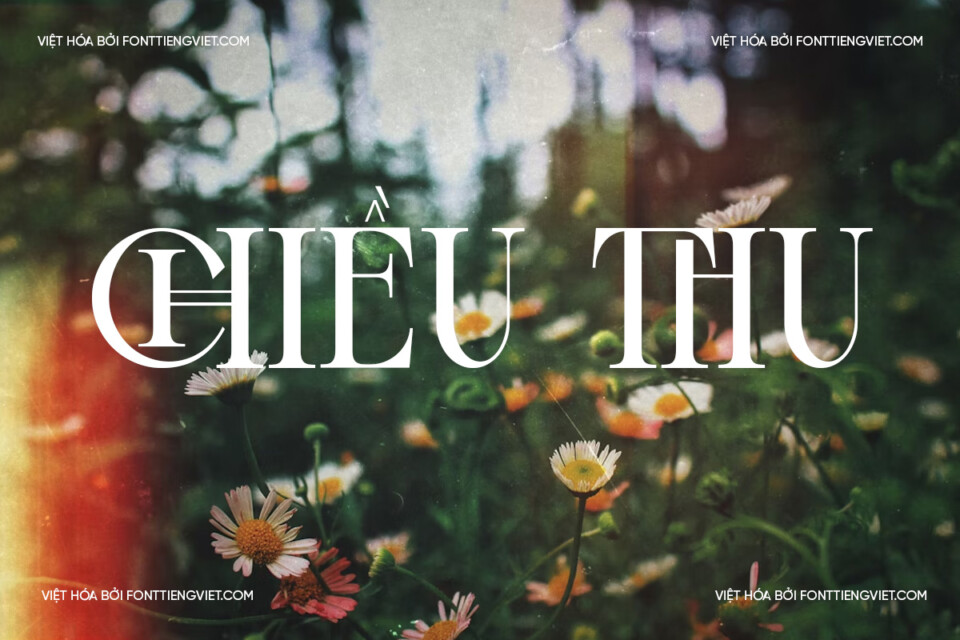
Font Việt hóa 1FTV VIP Lorenna
Chào mừng các bạn đến với thế giới sáng tạo nơi những con chữ không chỉ để đọc mà còn để cảm nhận vẻ đẹp nghệ thuật sâu sắc. Trong cộng đồng thiết kế đồ họa tại Việt Nam hiện nay, việc tìm kiếm một bộ Font Miễn Phí có hỗ trợ tiếng Việt hoàn chỉnh luôn là ưu tiên hàng đầu của các bạn học sinh và sinh viên. Hôm nay, chúng ta sẽ cùng khám phá bộ Font Việt hóa 1FTV VIP Lorenna, một siêu phẩm mang phong cách thanh lịch, hiện đại và vô cùng chuyên nghiệp. Đây là lựa chọn lý tưởng cho những ai đang muốn nâng tầm các bài thuyết trình, dự án học tập hay những ấn phẩm truyền thông cá nhân một cách tinh tế nhất.
Khám phá đặc điểm nổi bật của Font Việt hóa 1FTV VIP Lorenna
Bộ Font Việt hóa 1FTV VIP Lorenna được biết đến là một phông chữ thuộc phong cách Serif (có chân) nhưng lại mang hơi hướng đương đại rất rõ nét. Điểm đặc trưng của bộ font này chính là sự kết hợp hoàn hảo giữa những đường nét thanh mảnh và những nét đậm chắc chắn, tạo nên một tổng thể hài hòa và dễ nhìn trên nhiều nền tảng khác nhau.
Vẻ đẹp sang trọng và tính ứng dụng cao
Lý do khiến Font Việt hóa 1FTV VIP Lorenna trở nên “VIP” trong mắt người dùng chính là khả năng truyền tải thông điệp một cách lịch sự và trang trọng. Các ký tự được chăm chút kỹ lưỡng về khoảng cách (kerning), giúp cho việc trình bày văn bản trở nên thoáng đãng hơn. Đối với các bạn học sinh, bộ font này cực kỳ phù hợp để làm tiêu đề cho các báo cáo nghiên cứu hoặc thiết kế bìa sách bài tập. Sự tinh tế của Lorenna giúp người xem cảm thấy dễ chịu, đồng thời tạo ấn tượng về một sản phẩm có đầu tư và chỉnh chu về mặt hình thức.
Đã được tối ưu hóa cho tiếng Việt
Một trong những trở ngại lớn nhất khi sử dụng các font chữ nước ngoài là lỗi font khi gõ dấu tiếng Việt. Tuy nhiên, với phiên bản Font Việt hóa 1FTV VIP Lorenna, mọi vấn đề đã được giải quyết triệt để. Các dấu thanh như huyền, sắc, hỏi, ngã, nặng được đặt ở vị trí chuẩn xác, không bị đè lên chữ hay làm biến dạng cấu trúc của ký tự gốc. Điều này giúp cho quy trình thiết kế của bạn trở nên nhanh chóng và hiệu quả hơn bao giờ hết, đảm bảo nội dung văn bản luôn rõ ràng và chuyên nghiệp.
Hướng dẫn sử dụng Font Việt hóa 1FTV VIP Lorenna hiệu quả
Để phát huy tối đa vẻ đẹp của bộ font này, bạn cần lưu ý một số quy tắc nhỏ trong thiết kế. Đầu tiên, hãy sử dụng Font Việt hóa 1FTV VIP Lorenna cho các phần tiêu đề lớn hoặc các câu trích dẫn quan trọng để thu hút sự chú ý. Bạn có thể kết hợp nó với một font chữ không chân (Sans Serif) đơn giản cho phần nội dung chi tiết để tạo sự tương phản đẹp mắt.
Lưu ý khi phối màu và kích thước
Khi sử dụng Lorenna, hãy ưu tiên các tông màu trung tính như đen, xám đậm hoặc các màu pastel nhẹ nhàng để giữ được bản chất thanh lịch của chữ. Về kích thước, bộ font này hiển thị đẹp nhất ở size từ 18pt trở lên. Nếu bạn đang thực hiện các dự án cho nhà trường, việc sử dụng font chữ này sẽ giúp sản phẩm của bạn trông giống như một ấn phẩm tạp chí cao cấp, thể hiện tư duy thẩm mỹ hiện đại và sáng tạo của người thực hiện.
Kết luận về bộ font chữ Lorenna Việt hóa